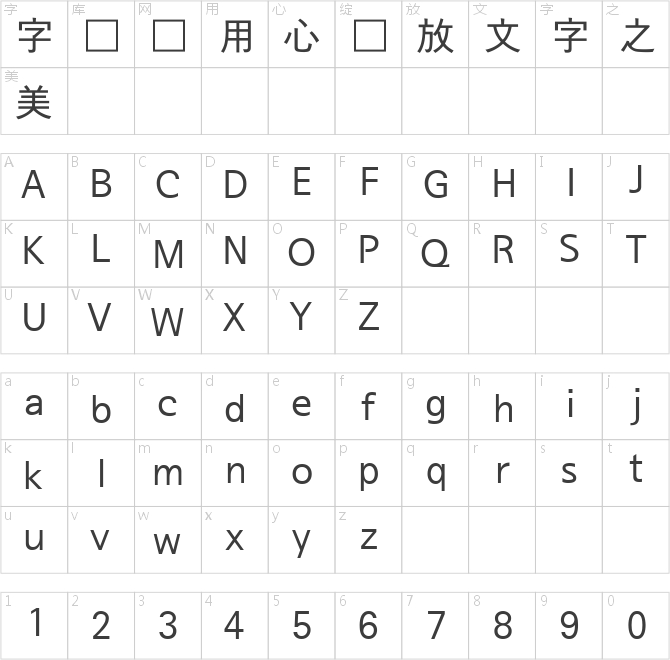
首爾南山體字體下載SeoulNamsan首爾南山體
首爾市為廣泛使用首爾的固有字體,提升城市認(rèn)同性與品牌價(jià)值而開發(fā)出明體系列的4種首爾漢江體(Light、Medium、Bold、Extra Bold)和哥特體系列的4種首爾南山體(Light、Medium、Bold、Extra Bold)、1種豎寫體等共9種首爾字體。
首爾字體中蘊(yùn)含著強(qiáng)韌的儒生精神與端莊的余白美,從造型上展現(xiàn)了韓屋的開放和瓦片的曲線美。此外,首爾字體取名時(shí)采用首爾兩大代表性資源“漢江”和“南山”,更能激發(fā)市民對(duì)韓民族固有美麗語(yǔ)言——韓文的文化自豪感。